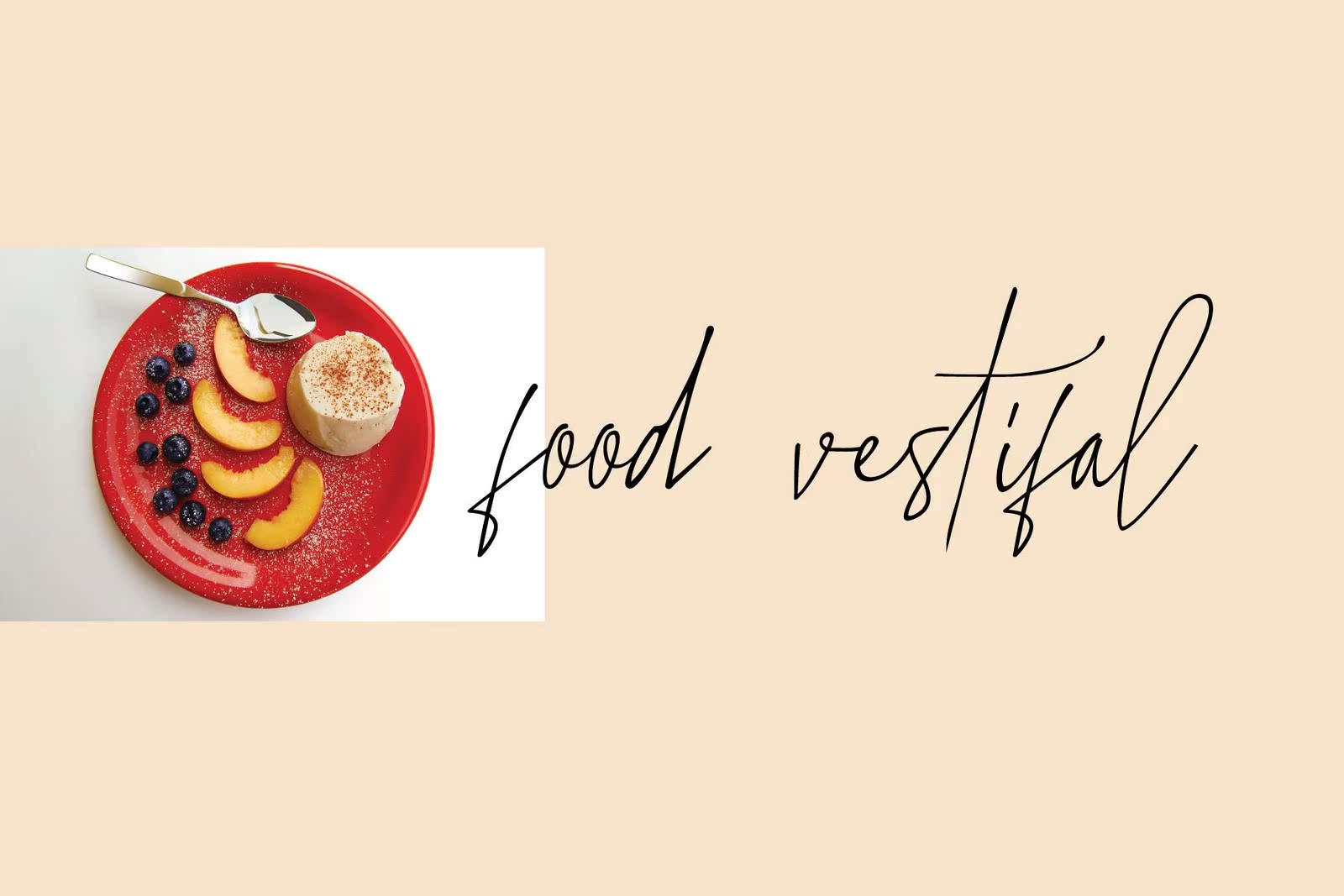
介绍静态字体、脚本字体。此字体来自MyAuthenticationHandwriting,以数字形式定义。适用于婚礼、食品菜单、时尚杂志、海报、徽标、水印、签名等的MicrolineHandwriting样式。此集合包括完整的柱式大写字母和小写字母、数字、,标点符号。此字体将为您提供真实的手写样式。此字体包括静态字体、脚本字体。此字体来自MyAuthentic手写体,以数字形式定义。适用于婚礼、食品菜单、时尚杂志、海报、标识、水印、签名等的MicrolineHandwriting样式。此设置包括全套大写字母和小写字母、数字、,标点符号。此字体将提供真实的手写样式。